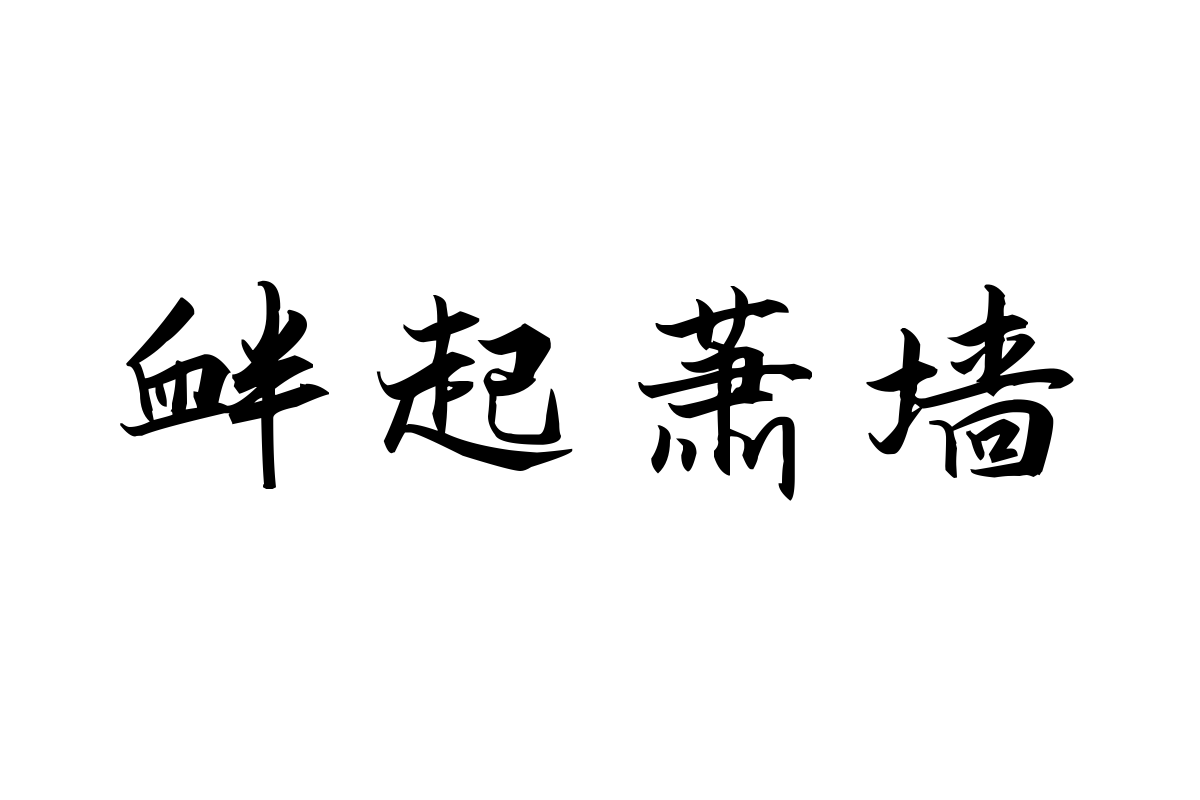
汉呈徐飞云毛笔字体是一组具有独特风格和特点的中文书法字体。该字体以其流畅、优雅的线条和独特的笔画结构而闻名,适合用于各种需要展示书法美感的场合。
汉呈徐飞云毛笔字体的特点包括:
1. 流畅的线条:该字体的笔画流畅自然,给人一种优雅的感觉。这使得它在书写和设计中都非常受欢迎。
2. 独特的笔画结构:与常见的毛笔字体相比,汉呈徐飞云毛笔字体在笔画结构上有一些独特的变化。这种变化使得字体看起来更加独特和有趣。
3. 易于识别:由于其独特的笔画结构和流畅的线条,汉呈徐飞云毛笔字体非常容易被识别和记忆。这使得它在各种应用场景中都非常实用。
4. 适用于多种场合:无论是用于个人签名、设计作品还是商业广告,汉呈徐飞云毛笔字体都能展现出其独特的魅力。
总之,汉呈徐飞云毛笔字体是一款非常实用的中文书法字体,适合用于各种需要展示书法美感的场合。